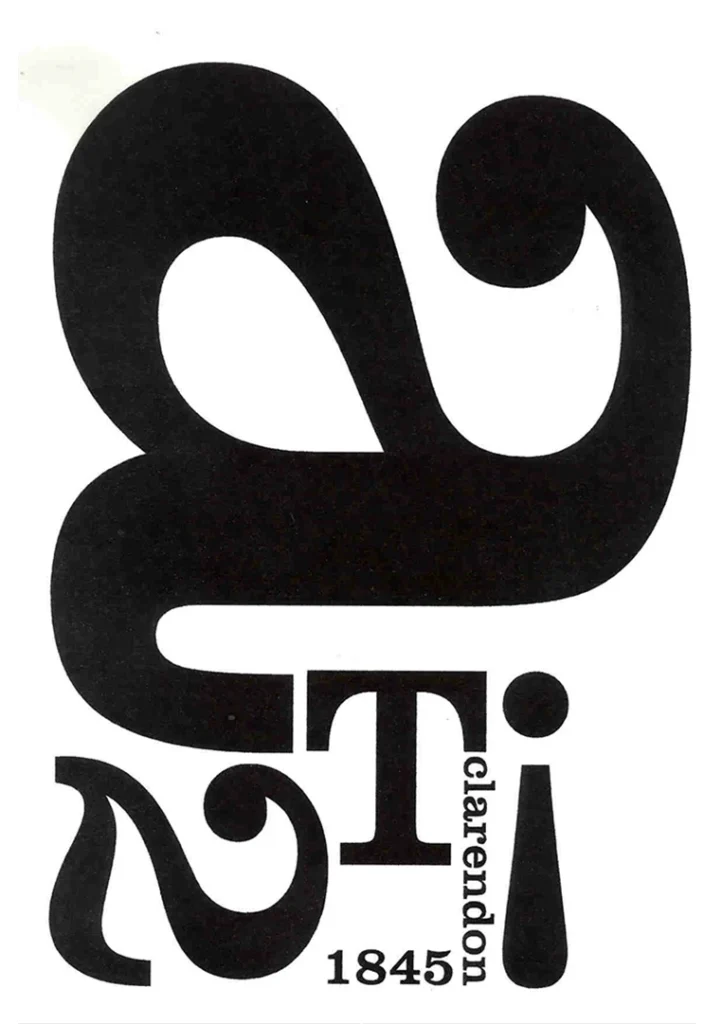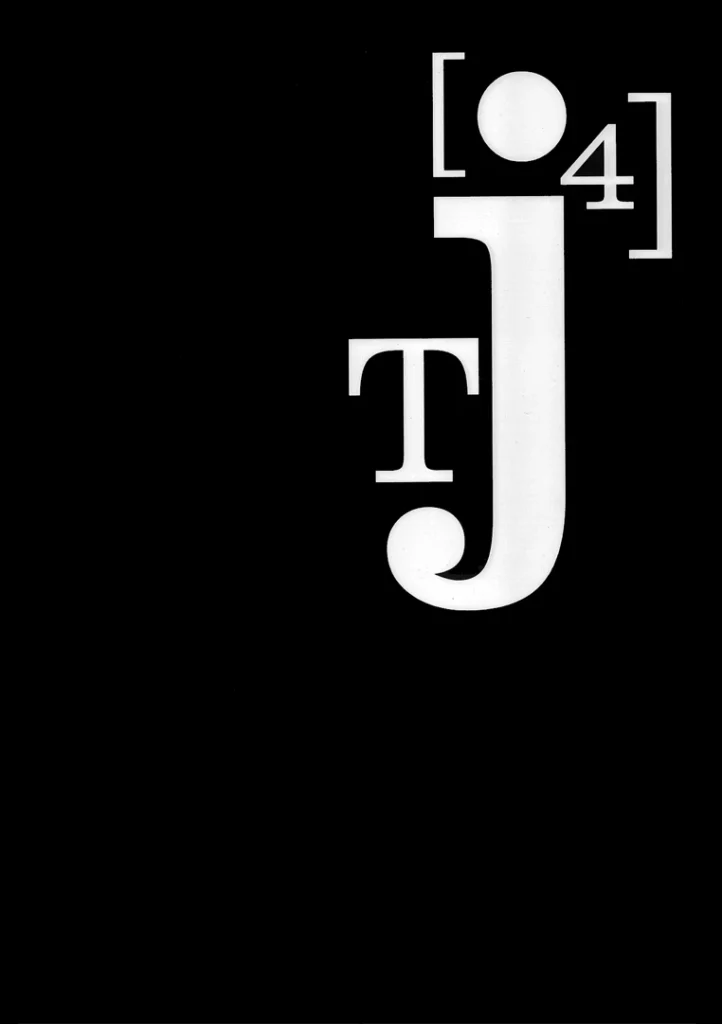
Es una slab serif creada en 1845 y se la atribuye a Robert Besley quien trabajaba en la fundición tipográfica Thorowgood and Co. Fue la primera tipografía registrada legalmente bajo la Ley de Copyright de Diseño del Reino Unido de 1842, lo cual fue un gran paso en la protección de derechos del diseño tipográfico.
Su apariencia inicial fue al de una letra condensada, y a diferencia de otros tipos egipcios, se emitió como tipo de texto y no para fines de publicidad. Es decir, fue diseñado para acompañar un tipo romano como una negrita que proporcionara énfasis donde fuera necesario. Para combinar con el romano, los serifs de Clarendon se unían con una curva a los trazos y a su vez estos presentaban cierto grado de contraste entre gruesos y finos.